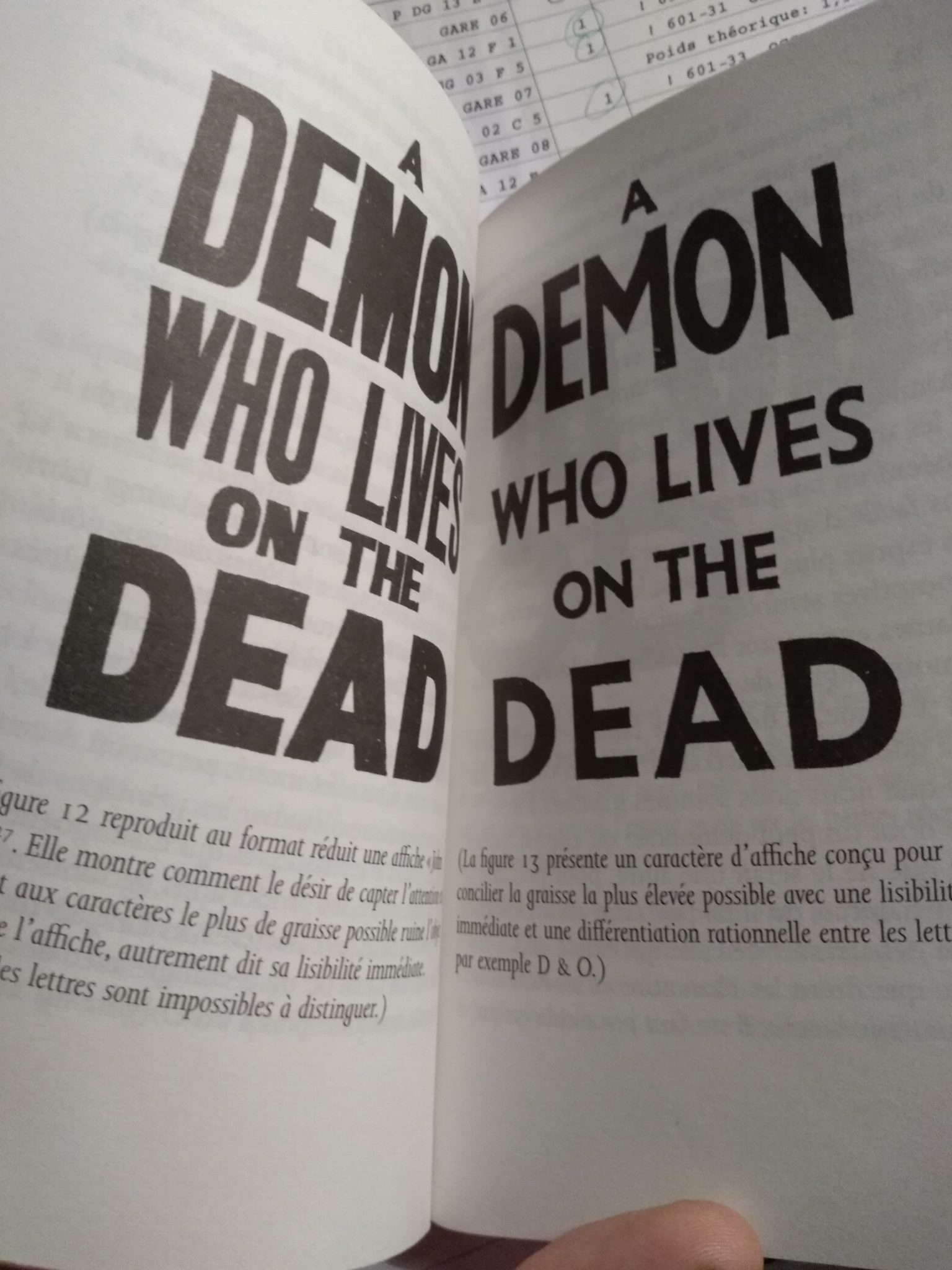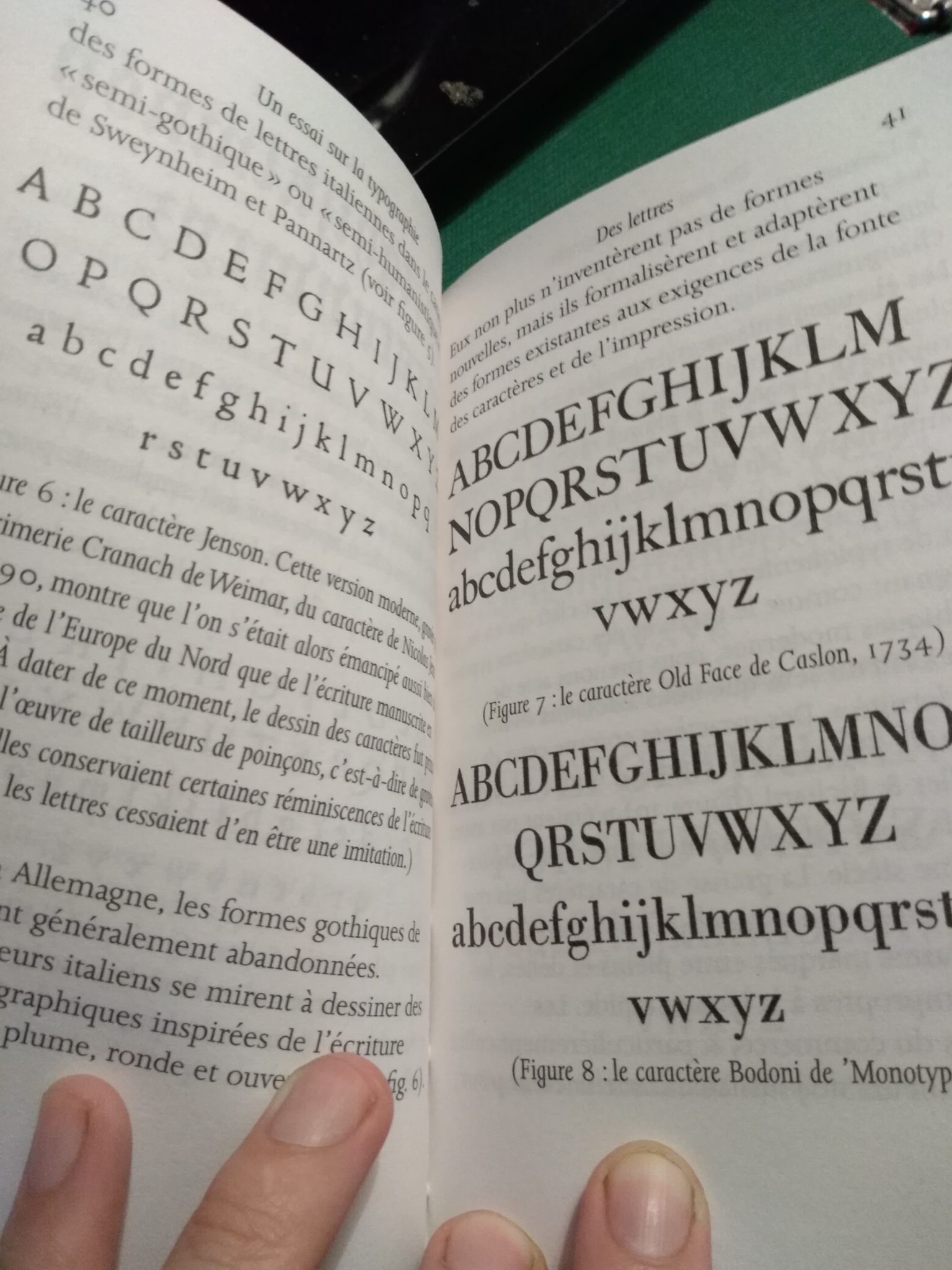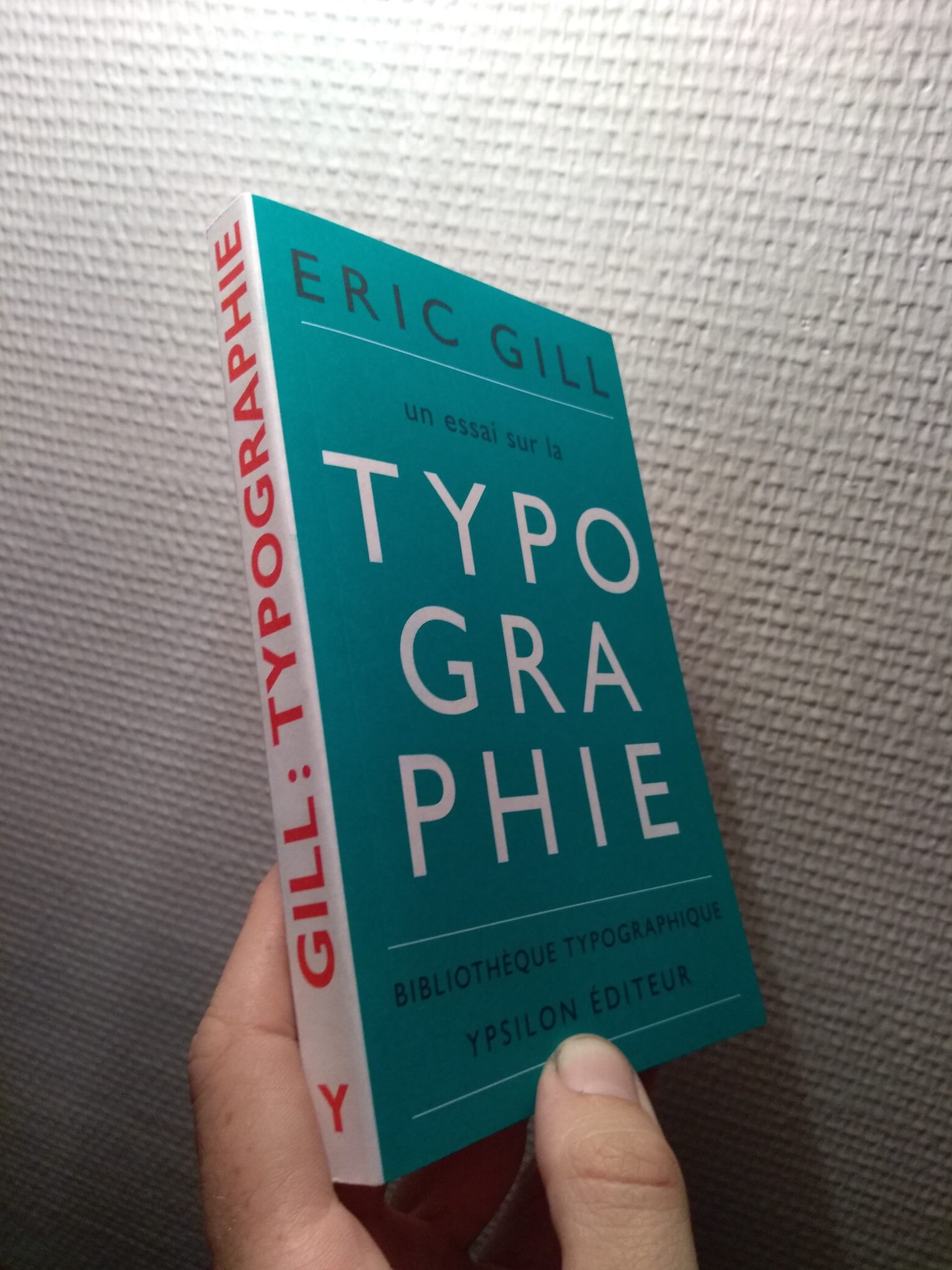
An Essay on Typography, publié en 1931 puis en 1936 dans une seconde édition révisée et augmentée, est l’ouvrage le plus connu de Gill. Il y étudie les méthodes de création et de production de la typographie : les formes des lettres, mais également la composition textuelle. Cet essai est continûment étayé par une réflexion sur les relations entre le travail manuel de l’homme, sa dimension créative, et sa mécanisation progressive et inéluctable, ainsi que sur les contradictions qu’elles ne manquent pas d’engendrer.
Traduit de l’anglais par Boris Donné et Patricia Menay
Postface de Sébastien Morlighem